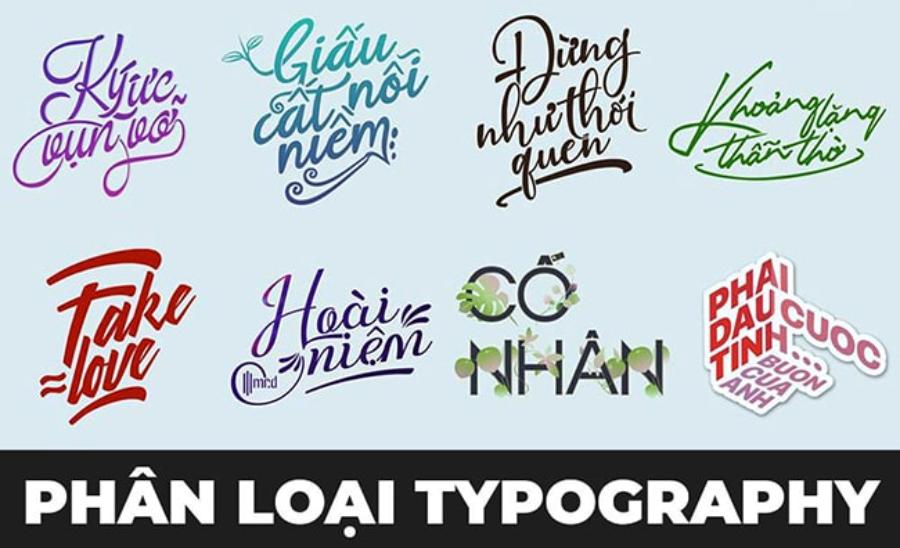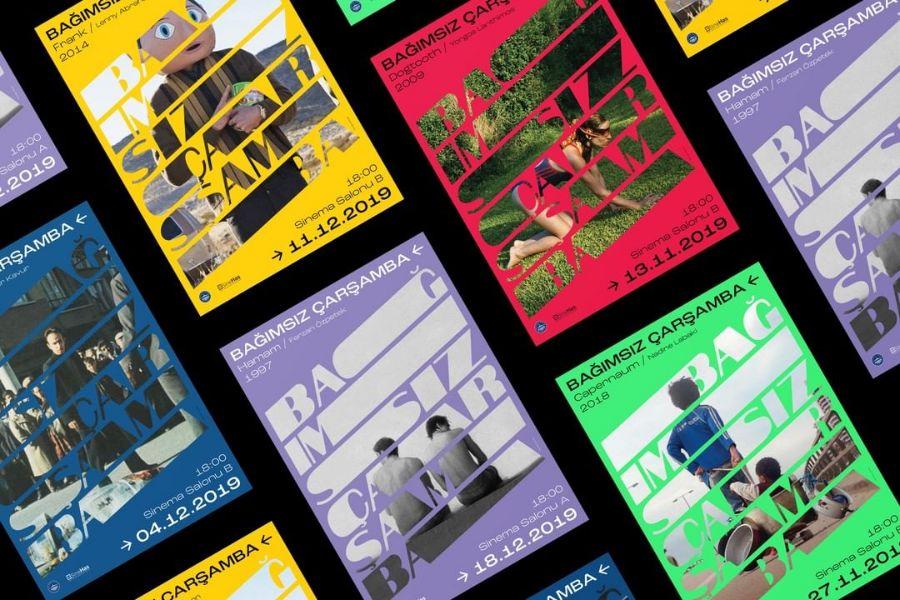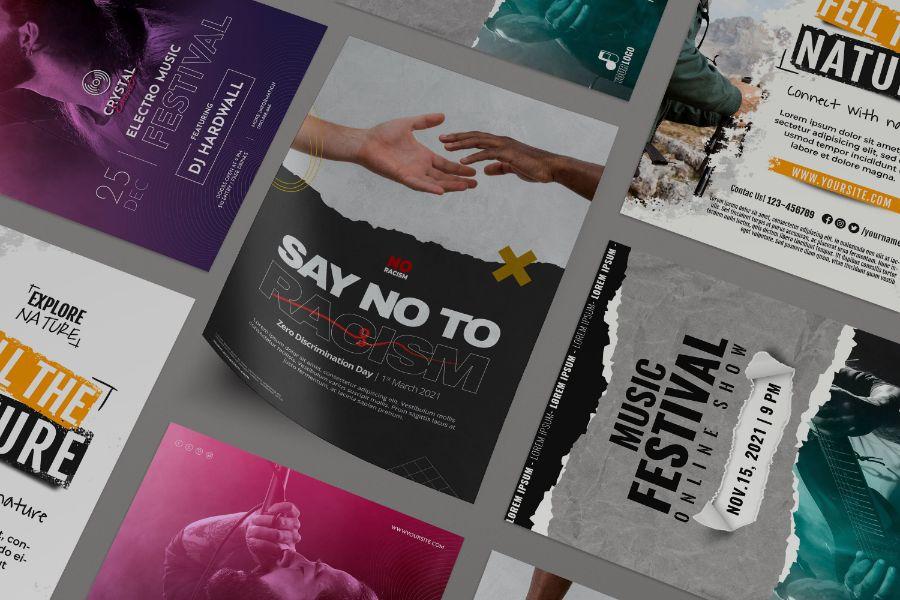
Khám Phá Font Chữ và Typography: Xu Hướng Thiết Kế 2025 Đầy Sáng Tạo
Khám phá khái niệm font chữ và typography, hiểu rõ sự khác biệt và cách áp dụng hiệu quả. Cập nhật xu hướng font chữ 2025 để thiết kế đồ họa “bắt trend” ấn tượng, chuyên nghiệp.
Khám Phá Font Chữ và Typography: Xu Hướng Thiết Kế 2025 Đầy Sáng Tạo
Trong thiết kế đồ họa, font chữ và typography đóng vai trò quan trọng không chỉ trong việc truyền tải thông điệp mà còn tạo dựng được dấu ấn độc đáo cho mỗi sản phẩm thiết kế. Hiểu đúng về font chữ và typography sẽ giúp các nhà thiết kế không chỉ nâng cao tính thẩm mỹ mà còn tối ưu hóa trải nghiệm người dùng. Cùng sadesign khám phá khái niệm và xu hướng font chữ 2025 để bạn luôn đi đầu trong việc thiết kế “bắt trend”.
1. Font Chữ và Typography: Khái Niệm Cơ Bản
Font chữ và typography là hai thuật ngữ quan trọng trong lĩnh vực thiết kế đồ họa và in ấn. Tuy có mối liên hệ chặt chẽ, nhưng chúng lại mang những đặc điểm và ứng dụng riêng biệt.
1.1. Font chữ là gì?
Font chữ (hay kiểu chữ) là một tập hợp các ký tự (chữ cái, chữ số, dấu câu,...) được thiết kế theo một phong cách thống nhất. Mỗi Font chữ có một tên gọi riêng (ví dụ: Arial, Times New Roman, Roboto,...) và thể hiện một cá tính, đặc điểm khác nhau. Font chữ không chỉ đơn thuần là công cụ để viết, mà còn là yếu tố thẩm mỹ, góp phần tạo nên vẻ đẹp và phong cách cho thiết kế.Mỗi font chữ có đặc trưng riêng, có thể là hiện đại, cổ điển hay phá cách.
1.2. Typography là gì?
Typography (hay nghệ thuật chữ) là việc lựa chọn và sắp xếp các Font chữ một cách khoa học, hài hòa để truyền tải thông điệp một cách hiệu quả và thẩm mỹ. Typography bao gồm việc lựa chọn Font chữ, kích thước chữ, khoảng cách giữa các chữ, dòng, đoạn văn, cũng như cách phối hợp chúng với các yếu tố thiết kế khác (màu sắc, hình ảnh, bố cục,...) để tạo ra một tổng thể hài hòa, ấn tượng. Typography là một nghệ thuật đòi hỏi sự am hiểu về Font chữ, nguyên tắc thiết kế, cũng như khả năng sáng tạo và thẩm mỹ của người thiết kế.
Typography bao gồm cả việc điều chỉnh khoảng cách giữa các chữ cái (kerning), khoảng cách giữa các dòng (leading), và cách sắp xếp văn bản trong một không gian thiết kế cụ thể.
Khái niệm typography bao quát hơn font chữ, vì nó còn liên quan đến cách thức kết hợp và phối hợp các font chữ trong một dự án thiết kế, tạo ra sự cân đối và dễ dàng cho mắt nhìn.
1.3. Mối quan hệ giữa Font chữ và Typography
Font chữ là "nguyên liệu", còn Typography là "công thức" để tạo nên một thiết kế chữ đẹp và hiệu quả. Font chữ cung cấp cho nhà thiết kế những kiểu chữ có sẵn, còn Typography giúp họ "nhào nặn", sắp xếp chúng một cách sáng tạo để đạt được mục đích giao tiếp và thẩm mỹ. Font chữ và Typography có mối quan hệ mật thiết, bổ sung cho nhau để tạo ra những tác phẩm thiết kế độc đáo, ấn tượng.
2. Lịch Sử Phát Triển Của Font Chữ và Typography
Font chữ và typography không phải là những khái niệm mới mẻ mà đã tồn tại từ rất lâu trong lịch sử. Từ những ngày đầu in ấn với các bản in thủ công, con người đã có nhu cầu sử dụng những kiểu chữ độc đáo để truyền tải thông điệp của mình.
• Thế kỷ 15: Johann Gutenberg phát minh ra máy in và bắt đầu sử dụng các font chữ dạng in (typefaces) đầu tiên.
• Thế kỷ 19: Sự phát triển của các font chữ in ấn, đặc biệt là khi các công ty như Linotype và Monotype cho ra đời các bộ font chữ hiện đại.
• Thế kỷ 20-21: Sự ra đời của font chữ kỹ thuật số đã mang đến một làn sóng sáng tạo trong typography, giúp các nhà thiết kế có thể tạo ra những kiểu chữ phù hợp với từng mục đích sử dụng.
Ngày nay, với sự phát triển mạnh mẽ của công nghệ, các công cụ thiết kế đồ họa giúp các nhà thiết kế dễ dàng lựa chọn và sáng tạo font chữ phù hợp cho mọi sản phẩm thiết kế, từ logo, website, đến các ấn phẩm in ấn.
3. Tầm Quan Trọng Của Font Chữ Và Typography Trong Thiết Kế
Trong bất kỳ dự án thiết kế đồ họa nào, font chữ và typography đóng vai trò quan trọng trong việc quyết định tính thẩm mỹ và khả năng truyền tải thông điệp. Việc lựa chọn font chữ không chỉ ảnh hưởng đến vẻ đẹp bề ngoài của thiết kế mà còn tác động đến cảm nhận và sự tiếp nhận của người xem.
Thẩm Mỹ và Chuyên Nghiệp: Font chữ tạo nên cái nhìn đầu tiên của người xem về thiết kế. Một font chữ đẹp và phù hợp sẽ khiến sản phẩm trở nên chuyên nghiệp và thu hút hơn. Ngược lại, một lựa chọn font chữ không phù hợp sẽ dễ dàng làm giảm chất lượng của sản phẩm thiết kế.
Tăng Cường Trải Nghiệm Người Dùng: Typography giúp tối ưu hóa sự dễ đọc và dễ hiểu của văn bản. Đặc biệt là trong các thiết kế web, việc sử dụng typography hiệu quả giúp người dùng dễ dàng tiếp cận thông tin và tạo cảm giác dễ chịu khi đọc.
Thể Hiện Thông Điệp: Font chữ có khả năng tạo dựng tính cách và phong cách cho sản phẩm. Một font chữ thanh thoát, nhẹ nhàng có thể thể hiện sự tinh tế, trong khi một font chữ đậm, mạnh mẽ có thể thể hiện sự quyết đoán, năng động.
• Sử dụng Typography: Sử dụng Typography sáng tạo để tạo ra những bài đăng, hình ảnh đẹp mắt, thu hút sự tương tác của người xem. Chú ý đến màu sắc, kích thước, vị trí của chữ để tạo ra hiệu ứng tốt nhất.
8. Kết Luận
Font chữ và typography không chỉ đơn thuần là công cụ giúp chúng ta viết chữ mà còn là một phần không thể thiếu trong việc xây dựng thương hiệu và truyền tải thông điệp trong thiết kế đồ họa. Việc nắm vững khái niệm và ứng dụng typography sẽ giúp các nhà thiết kế tạo ra những sản phẩm ấn tượng và thu hút người xem.